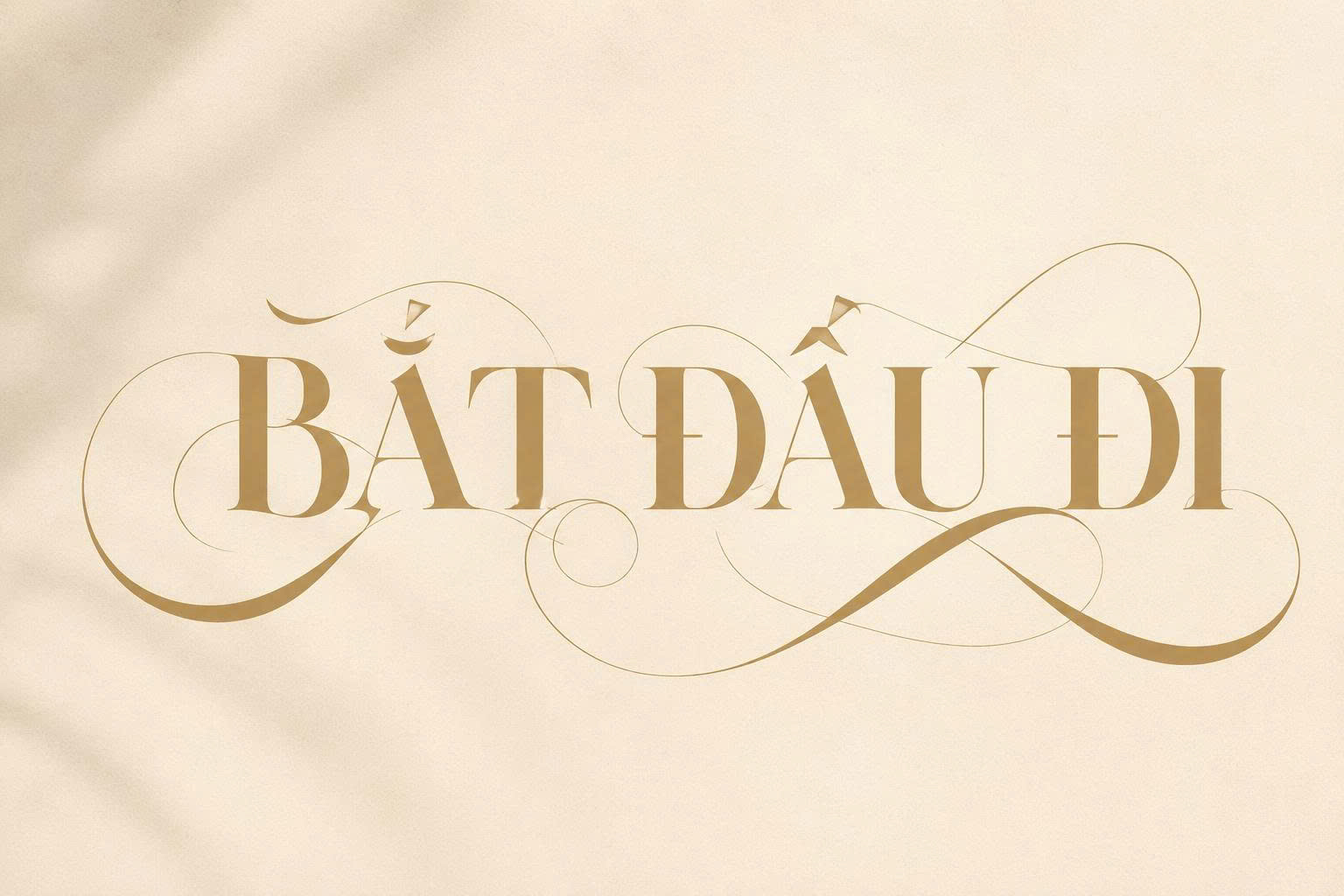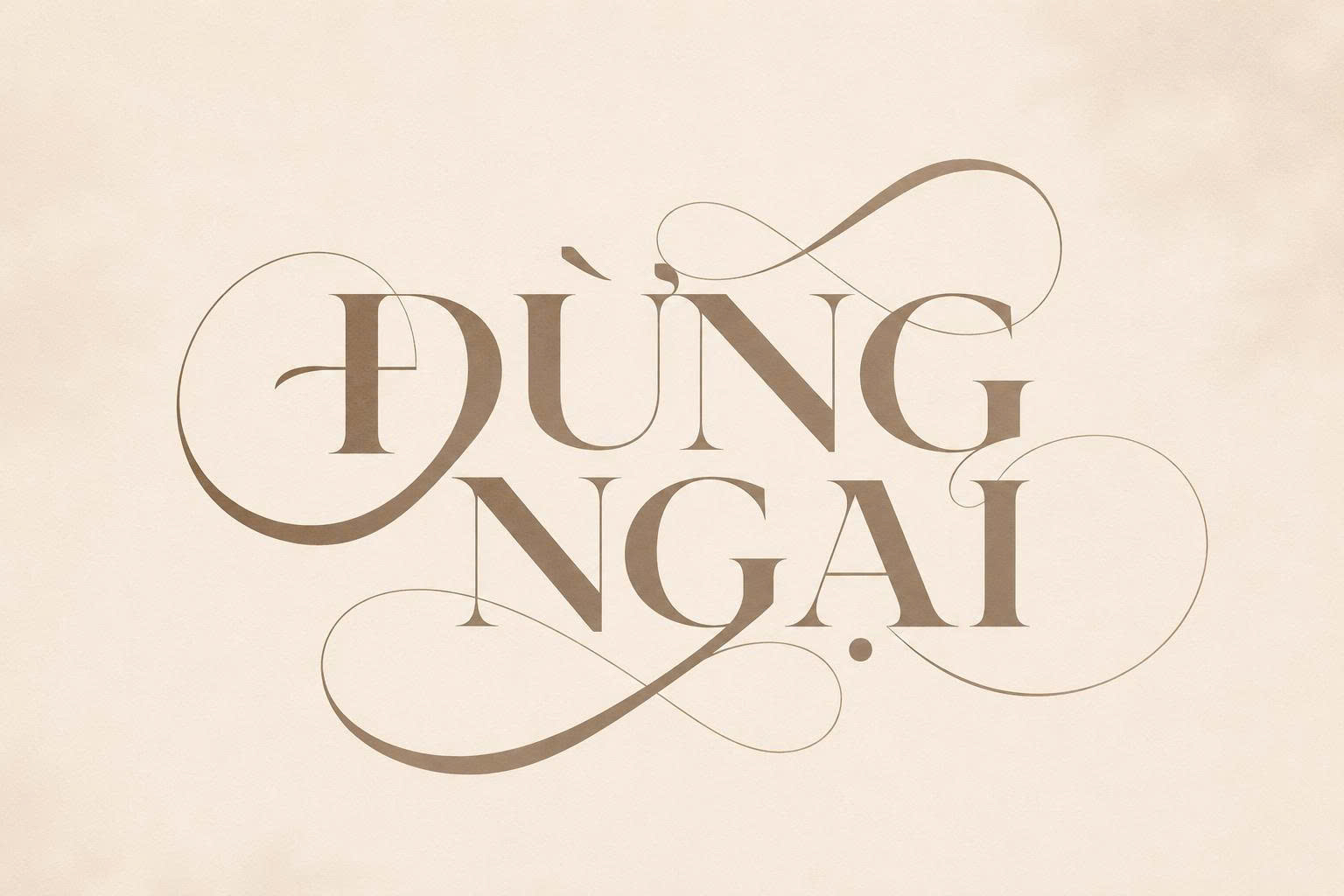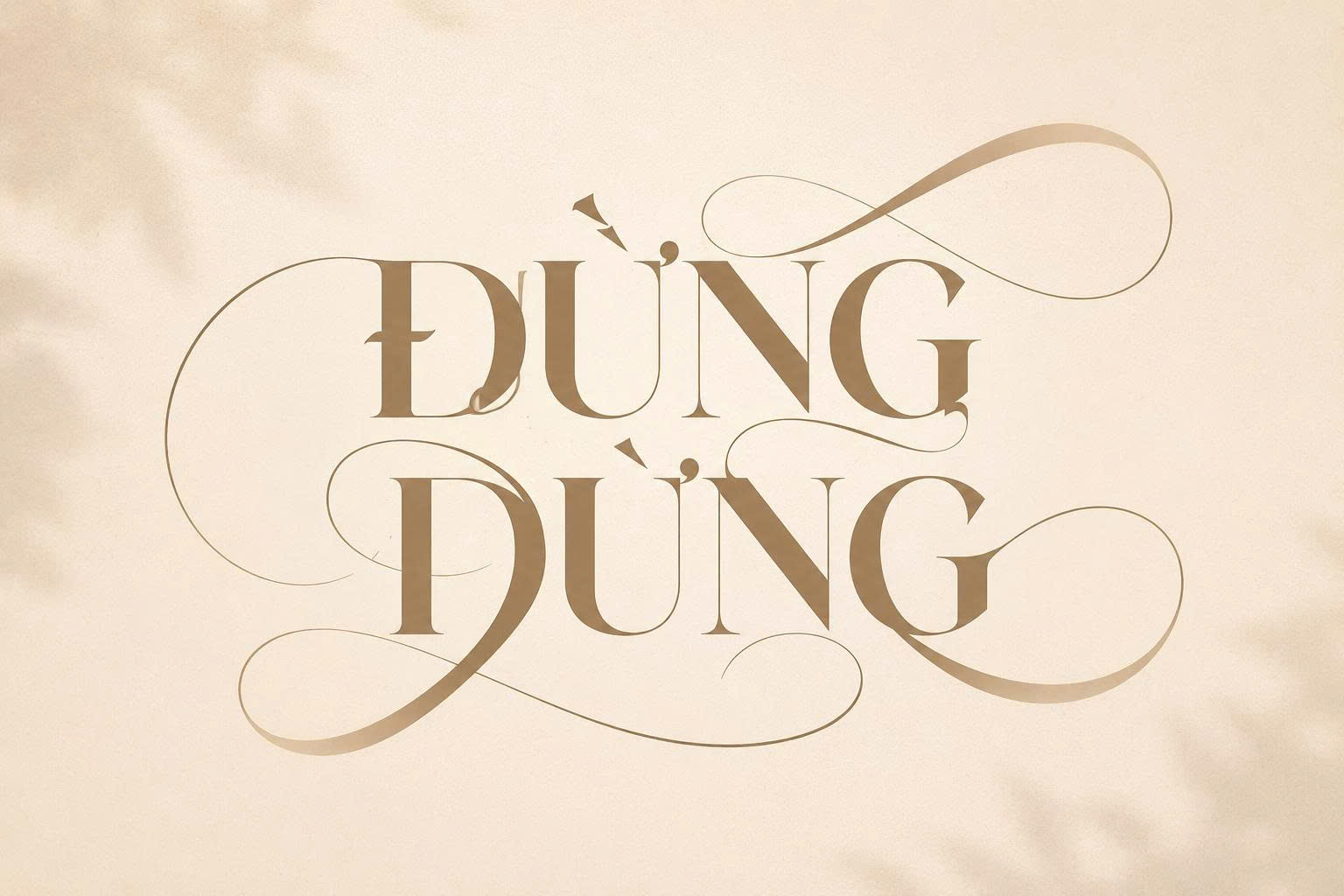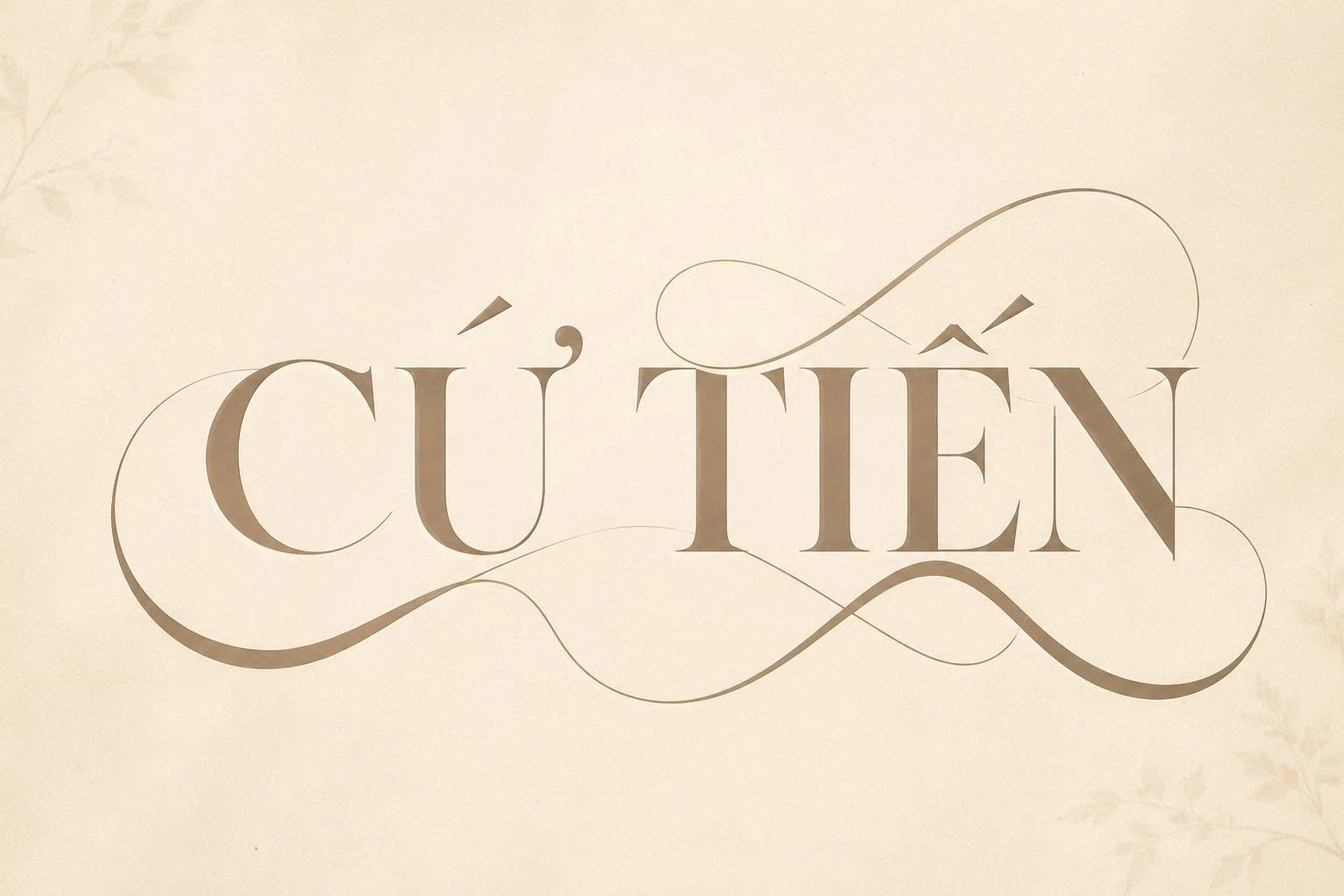
Font SVN Giaza Việt hóa là bộ phông chữ có chân (Serif) mang phong cách hiện đại, thanh lịch và vô cùng quý phái. Với đặc trưng là độ tương phản nét thanh đậm cực lớn kết hợp cùng những đường cong uốn lượn tinh tế, SVN Giaza đã trở thành lựa chọn hàng đầu cho các dự án thiết kế logo cao cấp, bao bì mỹ phẩm và nhận diện thương hiệu Luxury. Doozypack.vn cung cấp link tải font SVN Giaza chuẩn, giúp bạn sở hữu bộ phông chữ hoàn hảo, không lỗi dấu thanh để nâng tầm đẳng cấp cho mọi bản thiết kế.
Đặc điểm thiết kế tinh tế của font SVN Giaza Việt hóa
Giaza không chỉ là một phông chữ Serif thông thường; nó là sự tái hiện ngôn ngữ thời trang cao cấp dưới dạng ký tự đồ họa.
Phong cách Modern Serif sắc sảo và thời thượng
Đặc trưng lớn nhất của font SVN Giaza Việt hóa là sự đối lập mạnh mẽ giữa những nét dọc chắc khỏe và các nét ngang, nét nối thanh mảnh như sợi tóc (hairline). Cấu trúc chữ của Giaza gợi nhắc đến diện mạo của các tạp chí thời trang danh tiếng thế giới như Vogue hay Elle. Chính sự sắc sảo này mang lại cảm giác về một thương hiệu sang trọng, uy tín và có gu thẩm mỹ tinh tế ngay từ cái nhìn đầu tiên.
Hệ thống dấu tiếng Việt được tối ưu hoàn toàn
Nằm trong bộ sưu tập SVN (Style Việt hóa) nổi tiếng, Giaza đã được tinh chỉnh bộ dấu tiếng Việt một cách cực kỳ chỉn chu. Các dấu sắc, huyền, hỏi, ngã, nặng được thiết kế thanh mảnh hài hòa với thân chữ gốc, đảm bảo không làm mất đi độ thoáng và nhịp điệu Typography sang trọng của font. Việc sử dụng font SVN Giaza Việt hóa giúp designer tiết kiệm tối đa thời gian xử lý hậu kỳ cho các tiêu đề bao bì.
Tại sao designer nên chọn font SVN Giaza cho thiết kế bao bì?
Trong ngành thiết kế và sản xuất bao bì tại Doozypack.vn, SVN Giaza luôn nằm trong nhóm các font chữ “quyền lực” nhờ những ưu điểm vượt trội:
- Tạo dấu ấn Luxury tức thì: Chỉ cần đặt tên thương hiệu bằng font Giaza, bao bì sản phẩm của bạn đã toát lên vẻ đắt tiền, phù hợp cho ngành mỹ phẩm, nước hoa và quà tặng cao cấp.
- Khả năng hiển thị sắc nét: Nhờ cấu trúc hình học chuẩn xác, Giaza duy trì được vẻ đẹp thanh thoát từ màn hình website đến khi xuất hiện trên chất liệu giấy thực tế.
- Dễ dàng phân cấp thông tin: Giaza hoạt động cực tốt khi làm tiêu đề chính (Heading) hoặc Logo, tạo điểm nhấn thu hút thị giác mạnh mẽ cho khách hàng.
Lời khuyên từ xưởng in: Vì Giaza có một số nét nối thanh mảnh như sợi tóc, khi bạn thiết kế in ấn trên giấy Ivory nhẵn mịn, font sẽ hiển thị cực kỳ đẹp. Tuy nhiên, nếu in trên giấy Kraft nhám thô, bạn nên hạn chế để kích thước chữ quá nhỏ (dưới 9pt) để tránh hiện tượng mất nét mực.
03 Ứng dụng thực tế của font SVN Giaza tại Doozypack.vn
Vẻ đẹp quý phái của Giaza mang lại hiệu quả thị giác đặc biệt trên các ấn phẩm thực tế do Doozypack.vn sản xuất:
- Hộp mỹ phẩm & Nước hoa: Sự kết hợp giữa font Giaza và kỹ thuật ép kim mờ (Matte Gold) trên nền hộp đen hoặc trắng tạo nên diện mạo vô cùng đẳng cấp.
- Túi giấy thời trang cao cấp: Tên thương hiệu in bằng biến thể Bold của Giaza trên túi giấy Ivory cán màng mờ giúp khẳng định gu thẩm mỹ tinh tế của nhãn hàng.
- Thiệp mời & Menu sự kiện: Nét chữ Serif sắc sảo của Giaza là lựa chọn tuyệt vời cho các buổi tiệc tối trang trọng hoặc các dịch vụ Spa cao cấp.